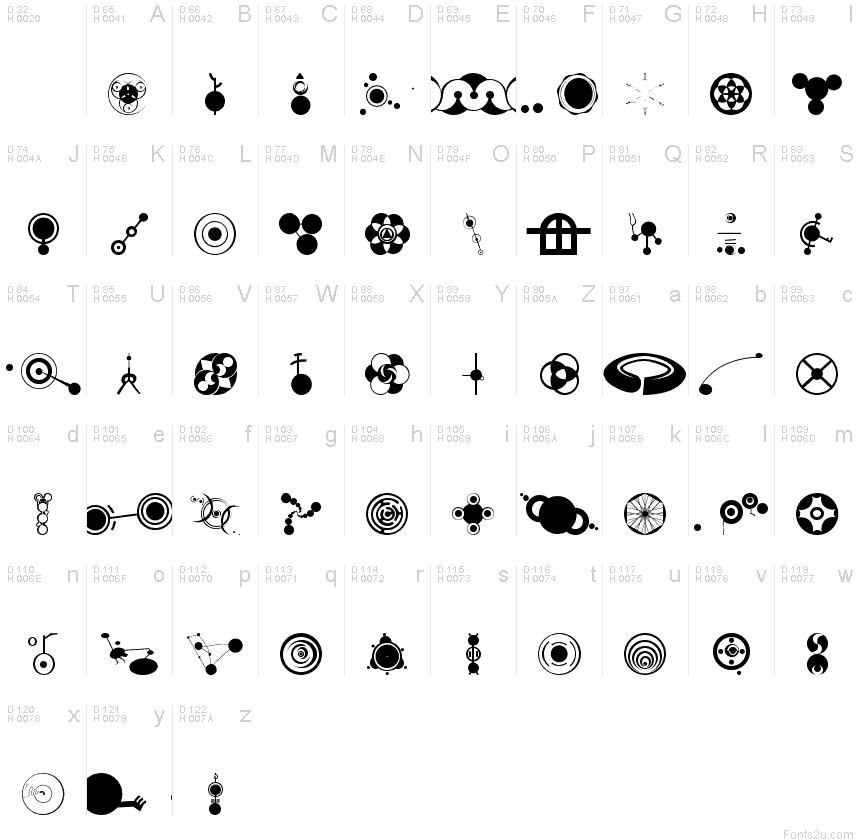
CropBats AOE od Astigmatic to darmowy, eksperymentalny font typu dingbat, który zamienia litery w tajemnicze symbole – kręgi w zbożu, diagramy orbit, lewitujące dyski i dziwne skupiska glifów. Znaki wyglądają wyrazistym, „tłustym” drukiem, jakby zostały przybite do strony z innej planety, a okręgi i linie łączą się w niepokojące konstelacje, które natychmiast przywodzą na myśl UFO i tajne transmisje.
Ten darmowy krój pisma świetnie sprawdzi się na plakatach sci-fi, zinach o tematyce konspiracyjnej, interfejsach gier, okładkach albumów, ulotkach, naklejkach i grafikach na koszulkach, gdzie chcesz uzyskać efekt zakodowanego, nieziemskiego języka. Użycie CropBats AOE jako przerysowanych ikon w połączeniu z czystym, geometrycznym krojem bezszeryfowym dla głównego tekstu zapewnia czytelność projektu, podczas gdy same symbole budują całą intrygę.